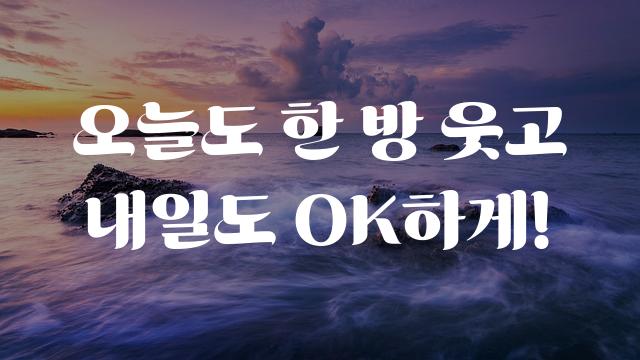
읏맨-엉뚱체는 OK금융그룹에서 제작한 폰트로, 장식체의 귀여움과 독특함이 동글동글한 형태로 표현되어 있습니다. 사용자에게 즐거움과 편안함을 전달하는 디자인입니다.
읏맨-엉뚱체은(는)
복실복실, 별모양/패턴, 둥근 스타일, 부드러움, 자연감성, 감성적인, 장식 스타일, 귀여운 스타일 계열의 생김새를 가지고 있으며
포스터, 소셜 미디어, 디지털 광고 등에서 자주 활용되며, 효과적인 메시지 전달에 적합합니다.
이 폰트는 광고/마케팅, 엔터테인먼트, 소매/유통 분야에 잘 어울리며,
재미있는, 창의적인, 귀여운 느낌을 담고 있는 것이 특징입니다.